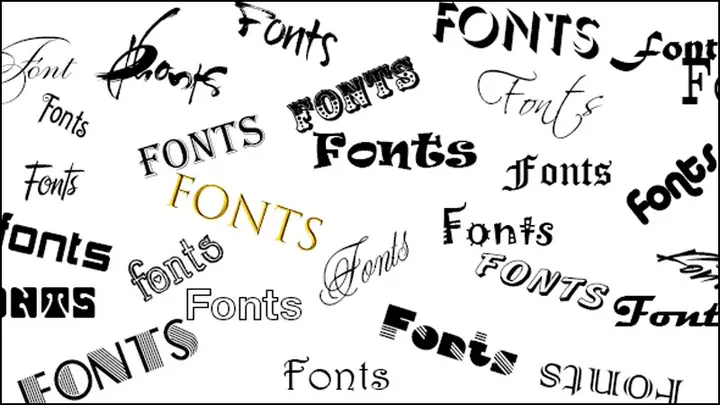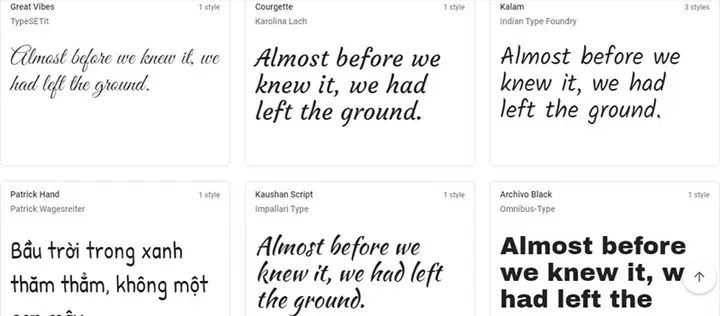
Việc lựa chọn font chữ đẹp cho máy tính không chỉ đơn thuần là vấn đề thẩm mỹ mà còn là yếu tố then chốt ảnh hưởng đến trải nghiệm người dùng, khả năng đọc hiểu và thậm chí là ấn tượng chuyên nghiệp trong nhiều lĩnh vực. Từ những nhà thiết kế đồ họa chuyên nghiệp cho đến lập trình viên hay người dùng văn phòng, việc sở hữu và biết cách khai thác các bộ font chữ chất lượng là điều vô cùng cần thiết. Bài viết này sẽ đi sâu vào tầm quan trọng của font chữ, cách chọn lọc những bộ font phù hợp và quy trình cài đặt chi tiết trên các hệ điều hành phổ biến, giúp bạn tối ưu hóa không gian làm việc và sáng tạo của mình.
Tóm tắt nhanh: Các bước cơ bản để sở hữu font chữ đẹp
Để có thể tìm kiếm, lựa chọn và sử dụng hiệu quả các bộ font chữ đẹp cho máy tính, bạn có thể tham khảo quy trình tổng quan sau đây. Mỗi bước đều đóng vai trò quan trọng trong việc đảm bảo font chữ không chỉ đẹp mắt mà còn phù hợp với mục đích sử dụng và tương thích với hệ thống của bạn.
- Xác định nhu cầu sử dụng: Trước tiên, hãy tự hỏi bạn cần font chữ cho mục đích gì (thiết kế, lập trình, văn bản hành chính, giải trí) và phong cách nào bạn muốn hướng tới.
- Tìm kiếm các nguồn font uy tín: Khám phá các nền tảng cung cấp font chữ miễn phí hoặc trả phí có danh tiếng tốt, đảm bảo chất lượng và tính hợp pháp của font.
- Đánh giá chất lượng và tính tương thích: Kiểm tra kỹ lưỡng về khả năng đọc, sự đầy đủ của các ký tự (bao gồm tiếng Việt), và liệu font có hoạt động tốt trên hệ điều hành và các phần mềm bạn đang sử dụng hay không.
Tại sao lựa chọnfont chữ đẹp cho máy tínhlại quan trọng?
Font chữ là một yếu tố tưởng chừng nhỏ nhưng lại có tác động rất lớn đến cách thông tin được truyền tải và tiếp nhận. Một bộ font chữ đẹp cho máy tính không chỉ làm cho văn bản trở nên hấp dẫn hơn mà còn cải thiện đáng kể trải nghiệm đọc và thể hiện sự chuyên nghiệp của người sử dụng. Đặc biệt trong các lĩnh vực như thiết kế đồ họa, phát triển web hay marketing, việc chọn đúng font chữ có thể là điểm khác biệt giữa một tác phẩm bình thường và một tác phẩm gây ấn tượng mạnh. Font chữ phù hợp giúp thông điệp trở nên rõ ràng, dễ hiểu và thu hút hơn, từ đó tăng cường hiệu quả giao tiếp. Hơn nữa, font chữ còn góp phần xây dựng nhận diện thương hiệu, tạo nên phong cách độc đáo và khó quên cho bất kỳ dự án nào.
Ảnh hưởng đến trải nghiệm người dùng
Trải nghiệm đọc là một trong những khía cạnh quan trọng nhất mà font chữ tác động. Một font dễ đọc, có kích thước và khoảng cách hợp lý giữa các ký tự và dòng sẽ giúp người dùng tiếp thu thông tin một cách nhanh chóng và thoải mái. Ngược lại, những font chữ quá phức tạp, khó nhìn hoặc có khoảng cách không đều có thể gây mỏi mắt, khó chịu và khiến người đọc từ bỏ nội dung. Vì vậy, việc chọn font chữ đẹp cho máy tính cần phải ưu tiên tính rõ ràng và khả năng đọc được, đặc biệt là với các văn bản dài hoặc giao diện người dùng. Các nghiên cứu về tâm lý học thị giác cũng chỉ ra rằng font chữ có thể ảnh hưởng đến cảm xúc và thái độ của người đọc đối với nội dung.
Thể hiện cá tính và phong cách thiết kế
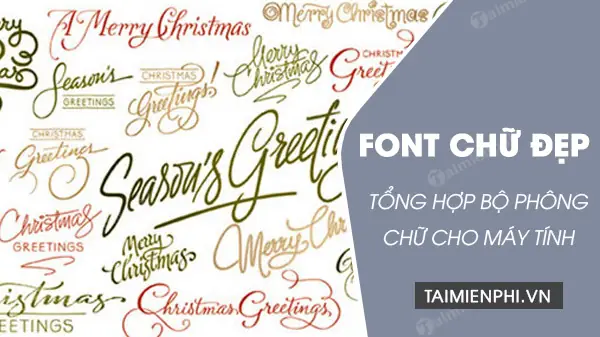
Mỗi font chữ mang một phong cách và cá tính riêng, từ sự trang trọng, cổ điển của các font Serif đến sự hiện đại, tối giản của font Sans-Serif, hay sự bay bổng, nghệ thuật của font Script. Bằng cách lựa chọn font chữ đẹp cho máy tính một cách có chủ đích, người dùng có thể thể hiện cá tính riêng, phong cách thiết kế độc đáo hoặc định vị thương hiệu của mình. Trong thiết kế đồ họa, font chữ không chỉ là văn bản mà còn là một phần của hình ảnh, góp phần tạo nên tổng thể hài hòa và chuyên nghiệp. Nó giúp truyền tải đúng thông điệp và cảm xúc mà người thiết kế muốn gửi gắm, từ đó tạo ra sự kết nối mạnh mẽ với đối tượng mục tiêu.
Tối ưu hóa khả năng đọc (Readability)
Khả năng đọc (readability) là mức độ dễ dàng mà người đọc có thể hiểu một văn bản. Đây là yếu tố cực kỳ quan trọng đối với mọi loại nội dung, từ bài blog, tài liệu kỹ thuật cho đến giao diện phần mềm. Một font chữ đẹp cho máy tính cần phải có khả năng đọc tốt, đảm bảo các ký tự được phân biệt rõ ràng ngay cả ở kích thước nhỏ. Các yếu tố như độ rộng của nét chữ, chiều cao của ký tự, khoảng cách giữa các chữ cái (kerning) và dòng (leading) đều ảnh hưởng đến readability. Chọn font có readability cao giúp người đọc dễ dàng quét qua nội dung, tìm kiếm thông tin cần thiết và không bị phân tâm bởi hình thức. Đây là một nguyên tắc cơ bản mà mọi chuyên gia thiết kế và người viết nội dung đều phải nắm vững.
Các yếu tố cần cân nhắc khi chọnfont chữ đẹp cho máy tính
Để chọn được font chữ đẹp cho máy tính phù hợp nhất, người dùng cần xem xét nhiều yếu tố khác nhau. Việc cân nhắc kỹ lưỡng các tiêu chí này sẽ giúp bạn đưa ra quyết định sáng suốt, đảm bảo font chữ không chỉ đáp ứng về mặt thẩm mỹ mà còn phục vụ tốt cho mục đích sử dụng cụ thể. Mỗi dự án hay nhu cầu cá nhân đều có những yêu cầu riêng biệt về font chữ, vì vậy hiểu rõ các yếu tố này là bước đầu tiên để tối ưu hóa không gian làm việc số của bạn. Hãy cùng Trần Du tìm hiểu chi tiết về các yếu tố này để đưa ra lựa chọn sáng suốt nhất.
Mục đích sử dụng (cá nhân, công việc, thiết kế đồ họa, lập trình)
Mục đích sử dụng là yếu tố hàng đầu quyết định loại font chữ đẹp cho máy tính mà bạn nên chọn. Nếu bạn là một nhà thiết kế đồ họa, bạn có thể cần một thư viện font phong phú với nhiều kiểu dáng sáng tạo, nghệ thuật để phục vụ cho các dự án quảng cáo, branding. Đối với lập trình viên, font chữ monospace (phong cách đơn cách) là lựa chọn tối ưu vì chúng giúp các ký tự có cùng độ rộng, dễ dàng đọc mã nguồn và phân biệt các dấu ngoặc. Trong khi đó, người dùng văn phòng thường ưu tiên các font Sans-Serif hoặc Serif truyền thống, rõ ràng, dễ đọc cho các tài liệu báo cáo, email. Mục đích sử dụng rõ ràng sẽ giúp bạn thu hẹp lựa chọn và tìm được font chữ hiệu quả nhất.
Việc lựa chọn và quản lý font chữ đẹp cho máy tính đòi hỏi sự cân nhắc kỹ lưỡng nhưng chắc chắn sẽ mang lại hiệu quả lớn cho công việc và trải nghiệm cá nhân của bạn. Từ việc xác định đúng mục đích sử dụng, tìm kiếm các nguồn uy tín, đến việc cài đặt và quản lý font một cách thông minh, mọi bước đều góp phần tạo nên một môi trường làm việc số tối ưu. Đừng ngần ngại thử nghiệm các bộ font mới để tìm ra phong cách phù hợp nhất với bạn.